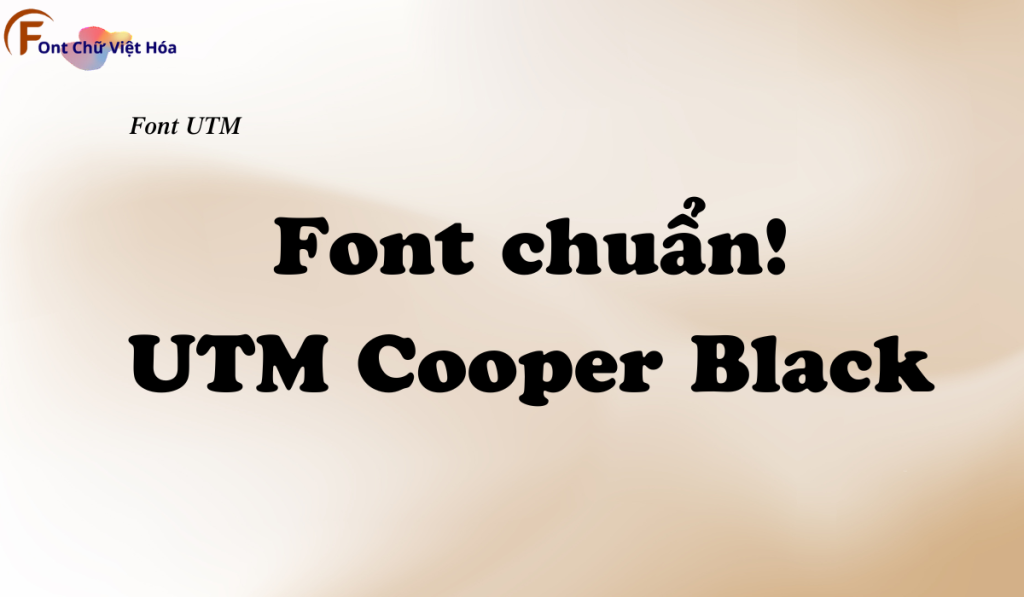
Font UTM Cooper Black Việt Hóa
Tác giả: UTM Cooper Black
Bộ Font: UTM
Kiểu chữ: Chữ có chân
Font UTM Cooper Black Việt Hóa là một font chữ có chân cá tính, thuộc bộ font UTM. Được thiết kế với mục tiêu mang lại sự độc đáo và sáng tạo, font này lý tưởng cho các dự án thiết kế như logo, poster, và bao bì sản phẩm. Với các nét chữ sắc nét và độ dày đều đặn, Font UTM Cooper Black Việt Hóa không chỉ dễ đọc mà còn tạo cảm giác hiện đại và phá cách. Việc Việt hóa font giúp người dùng dễ dàng tích hợp vào các thiết kế tiếng Việt, mang lại sự tiện lợi và nâng cao tính thẩm mỹ.